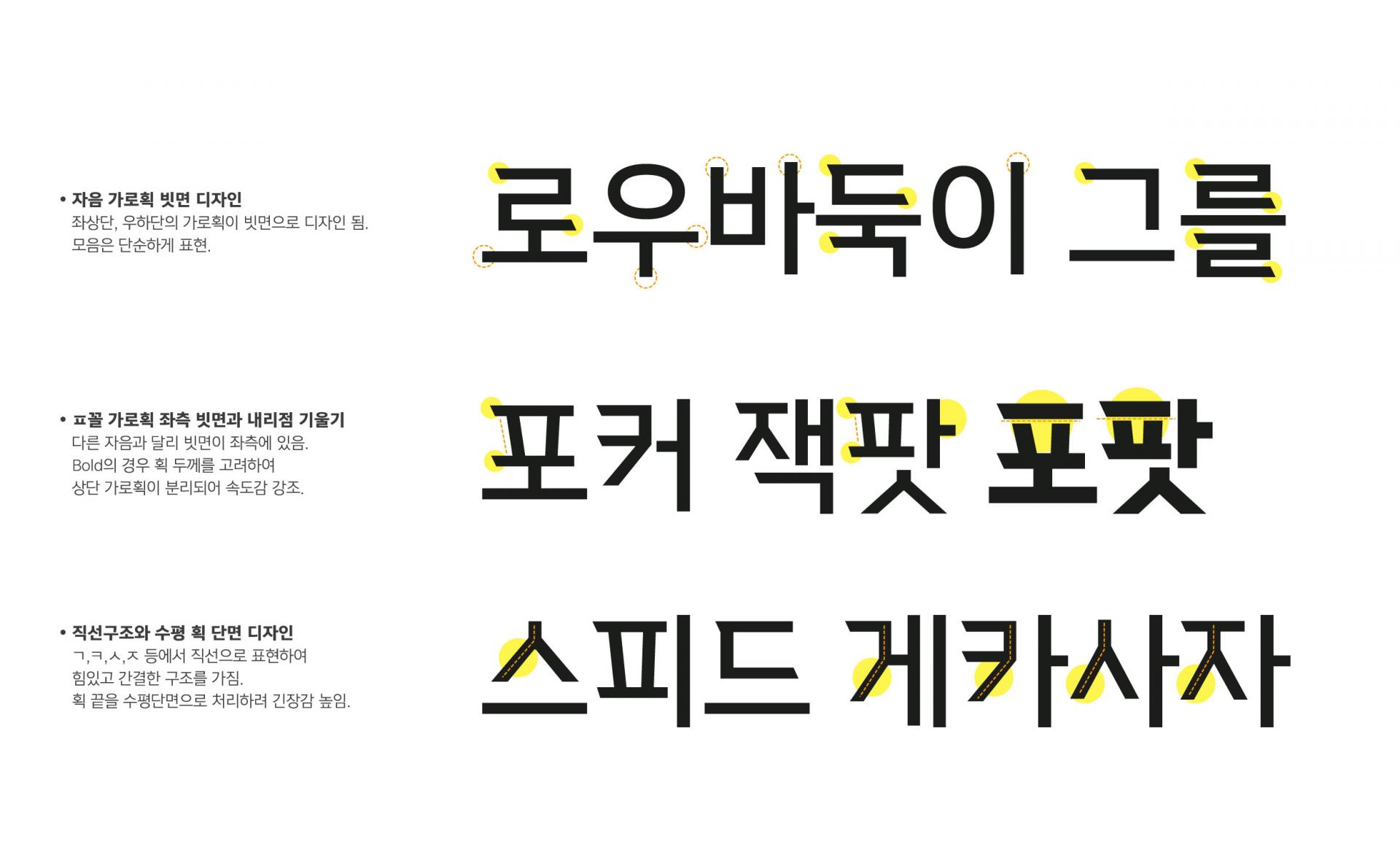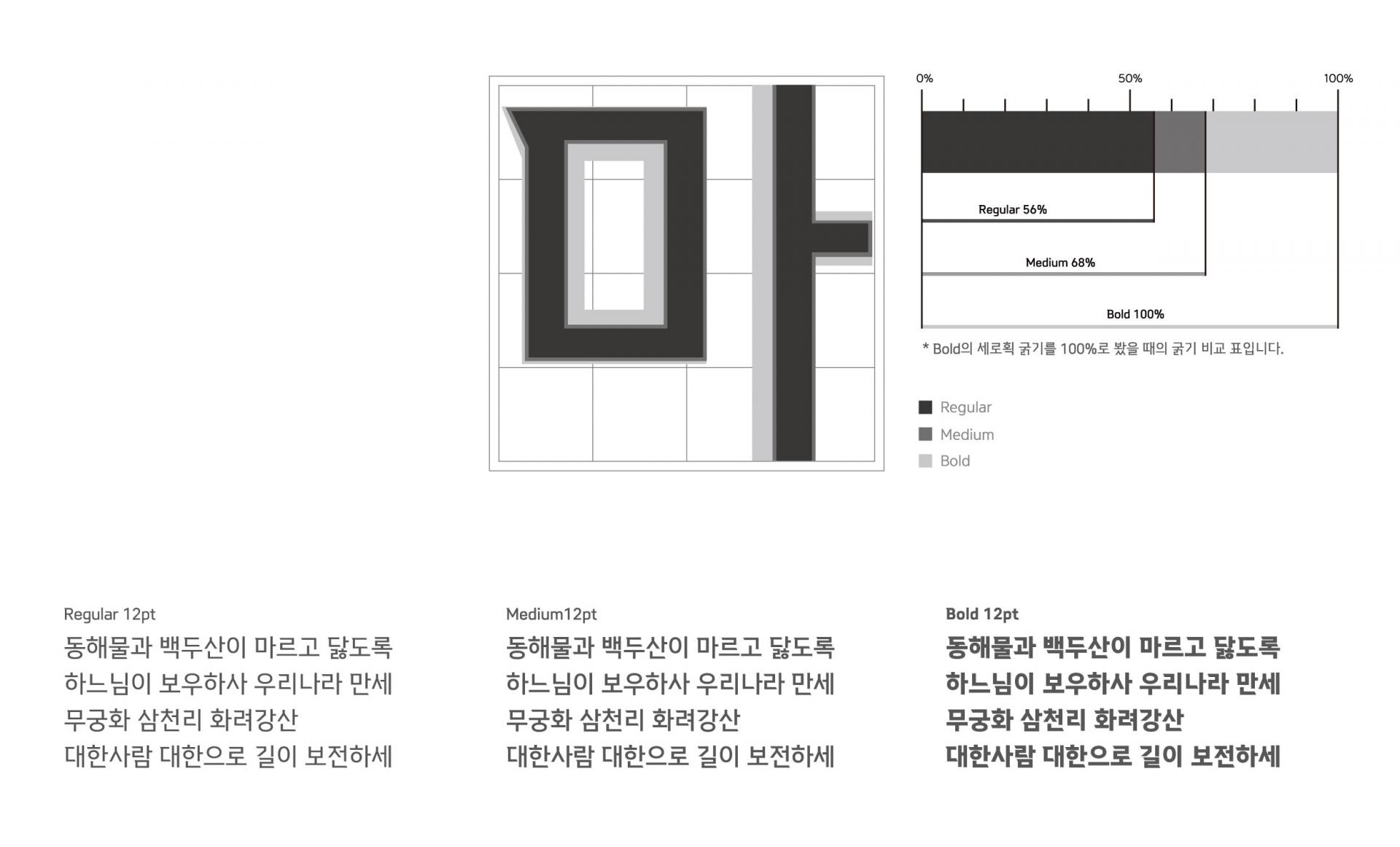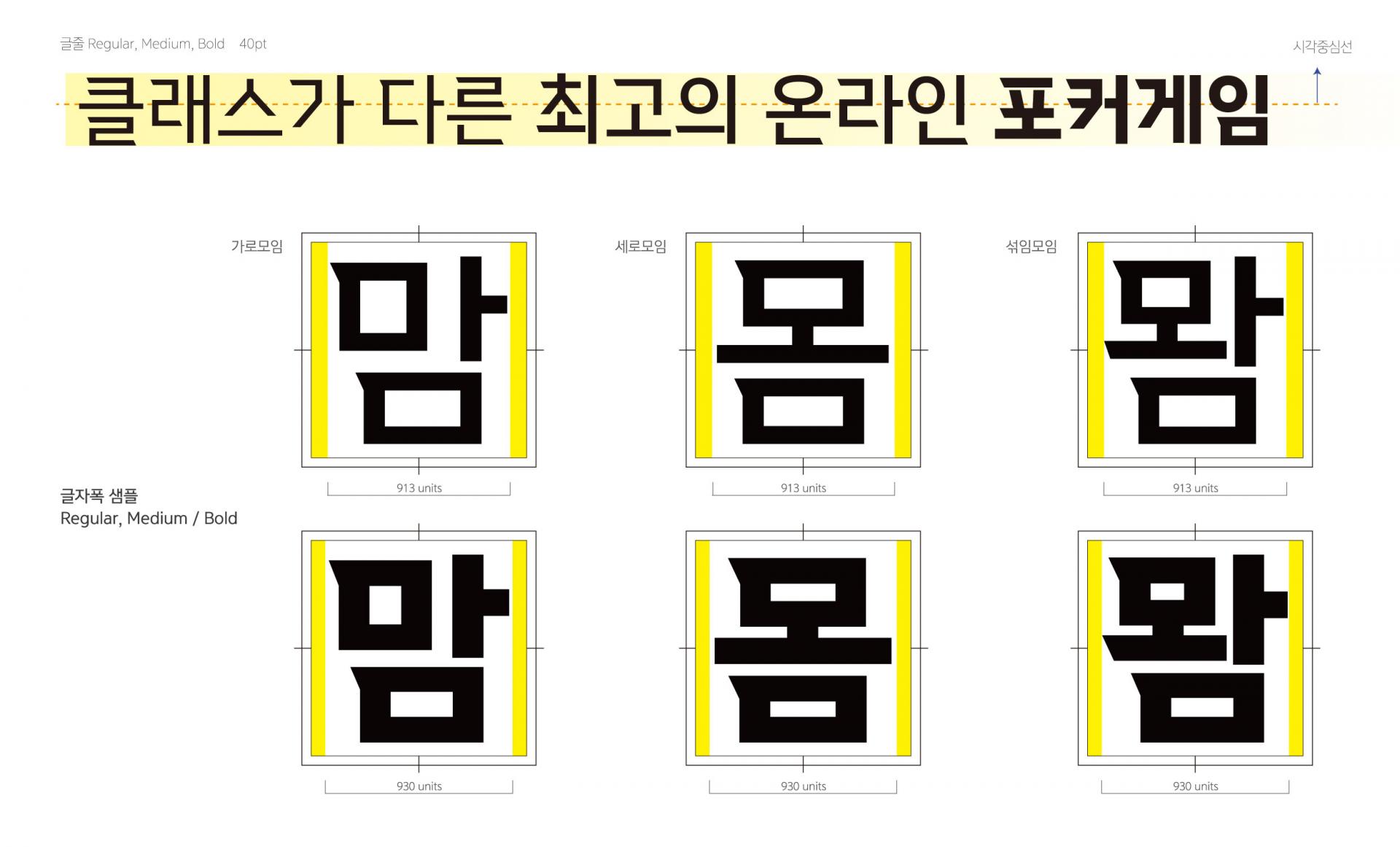
NHN [한게임포커]
NHN 한게임포커 전용서체는 빠르게 진행되는 포커 게임 속에서 플레이어가 느끼는 박진감과 긴장감을 담아냈다. 좌측 상단에서 우측 하단으로 기울어지는 대각선이 강조되는 자소의 형태와 곡선 대신 직선으로 표현되는 특징 등 속도감있게 진행되는 포커게임의 특성과 참여하는 플레이어의 빠른 판단력과 결단력을 상징한다.